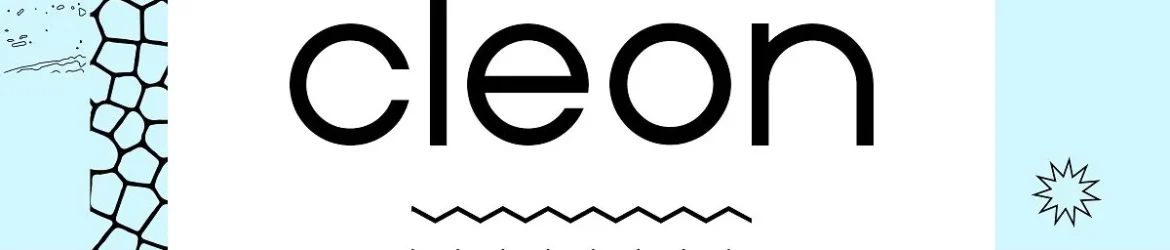
Introduzimos a Cleon! Ela é criada pelo Designer Factory738. Através desta sans serif tipo, você tem uma opção de design versátil para qualquer formato: web, impressão, gráficos em movimento, até mesmo materiais como posters e roupas personalizadas ou logomarcas. Com três versões de peso (regular, leve e bold), a Cleon vem equipada com letras maiúsculas e minúsculas para um visual completo. Ideal tanto para design gráfico moderno quanto para elementos mais tradicionais, a Cleon oferece uma combinação única que se destaca em qualquer projeto. Seja você um designer web ou impressão, a sua próxima criação pode beneficiar da elegância e simplicidade deste tipo de fonte.